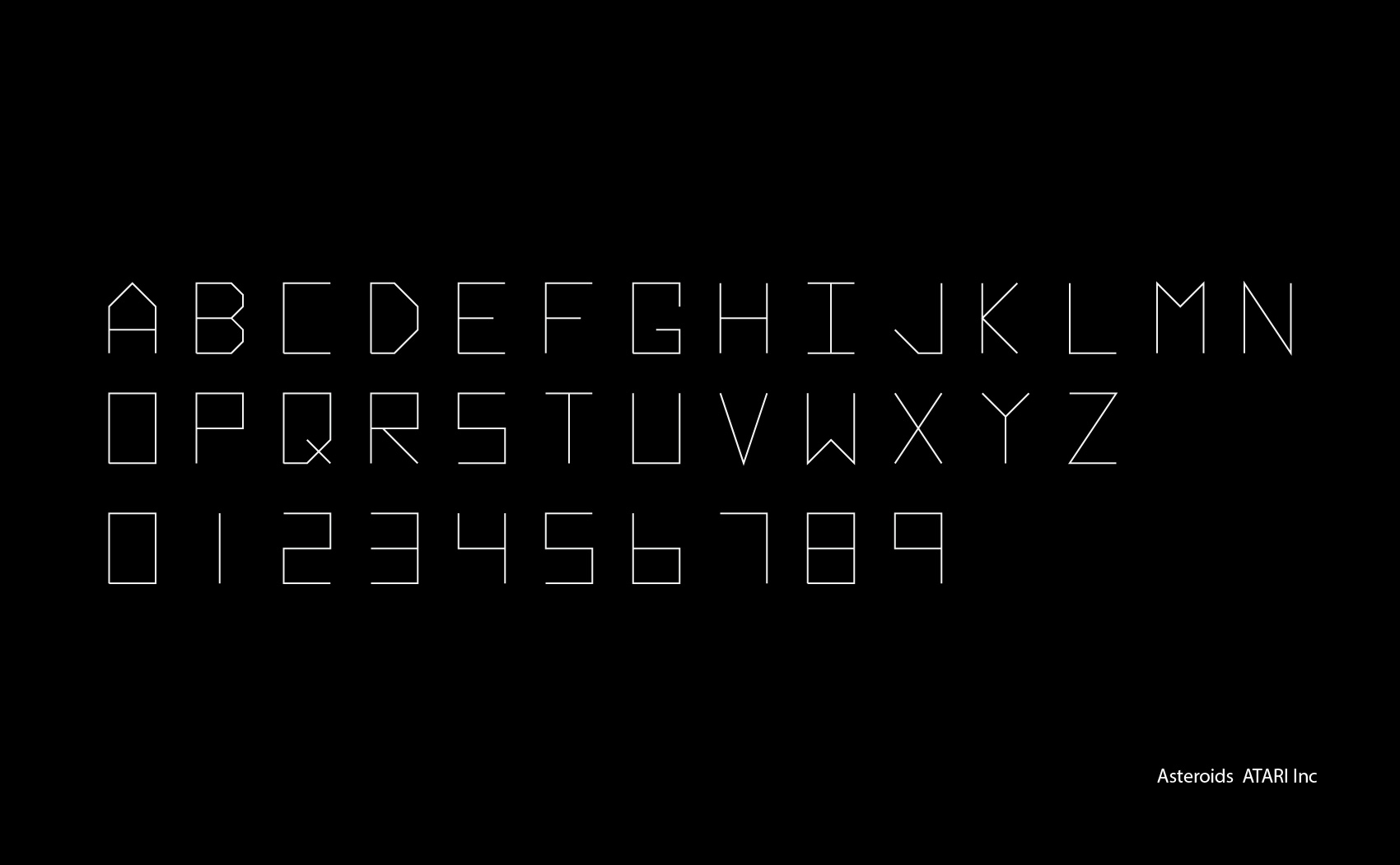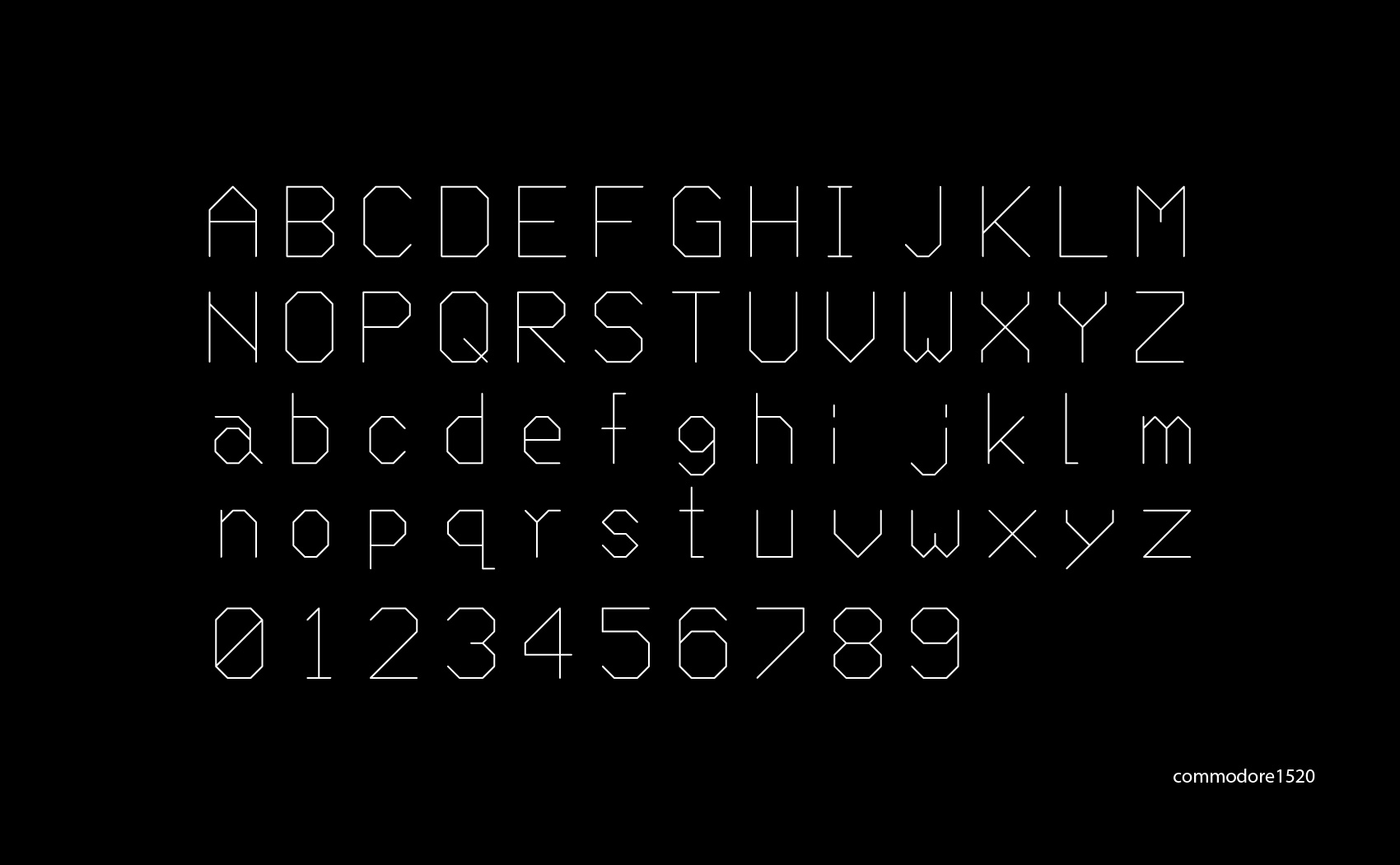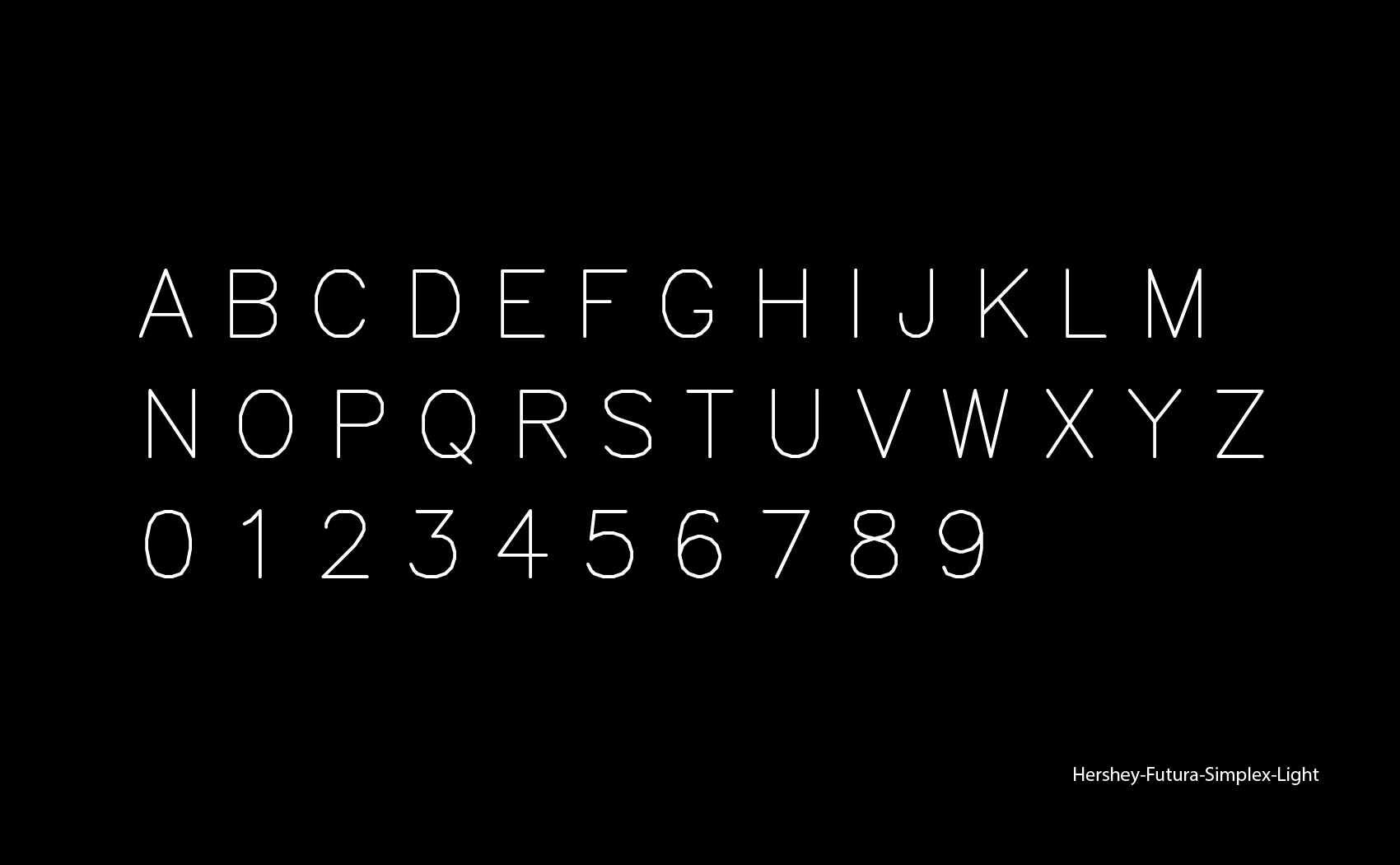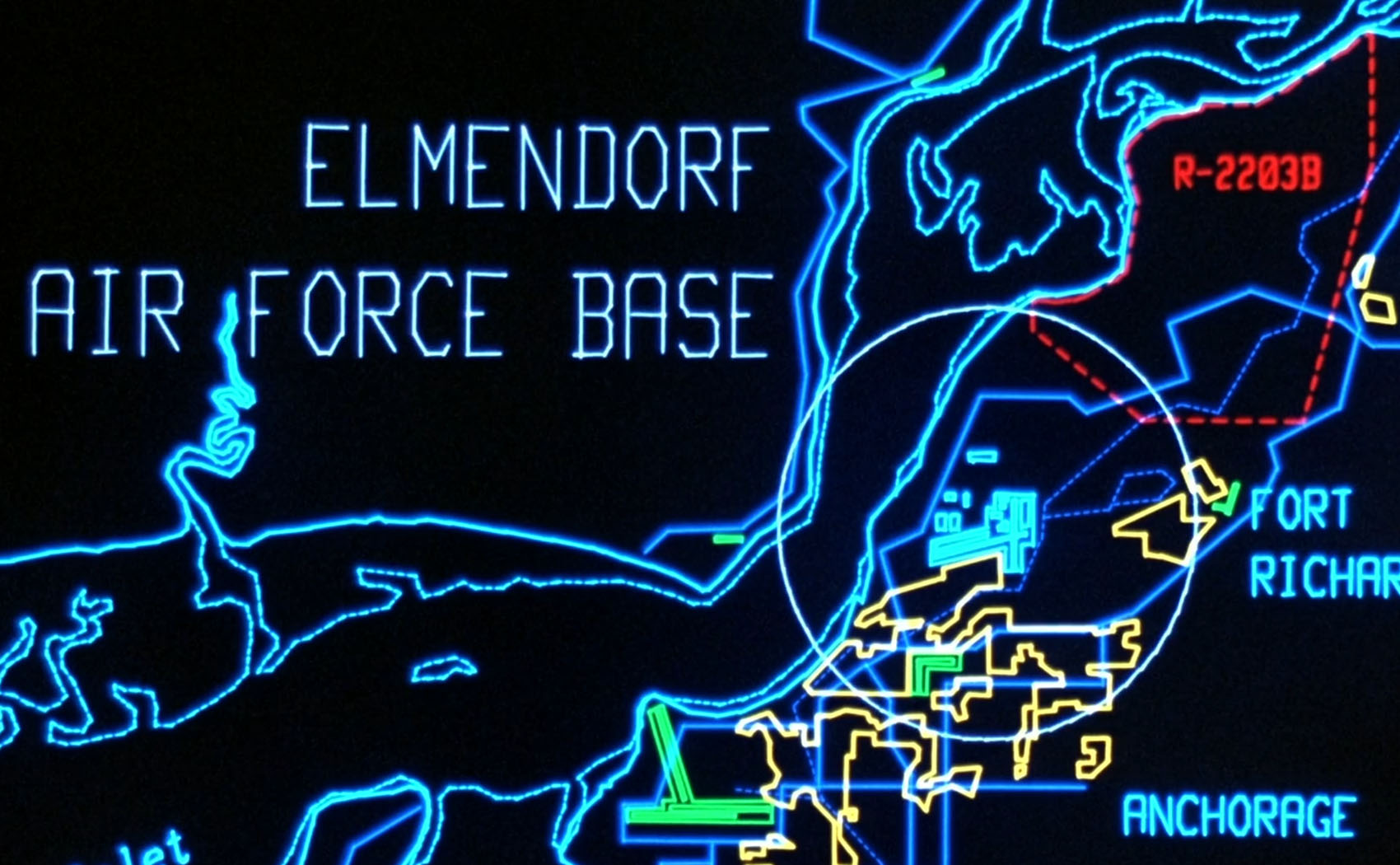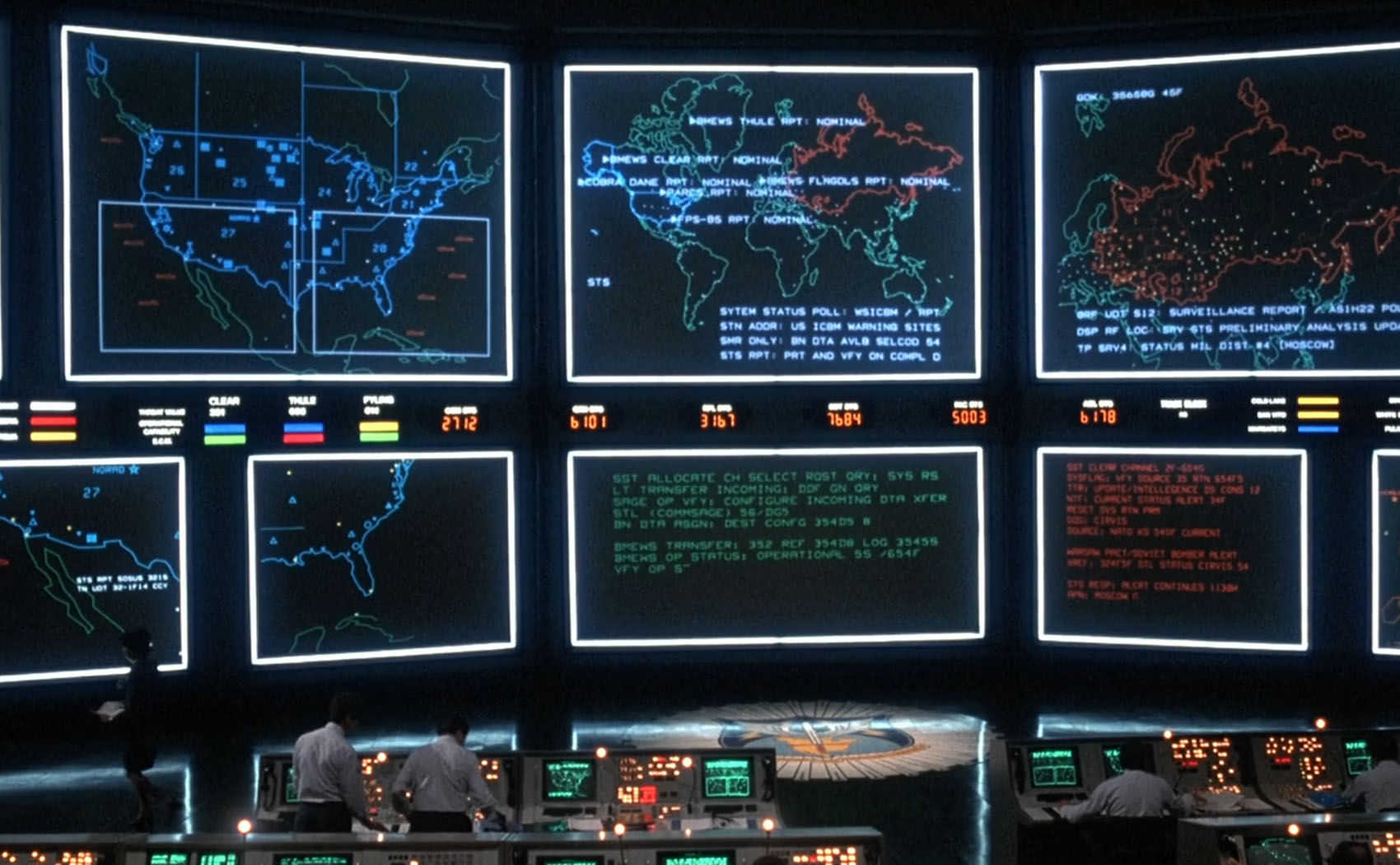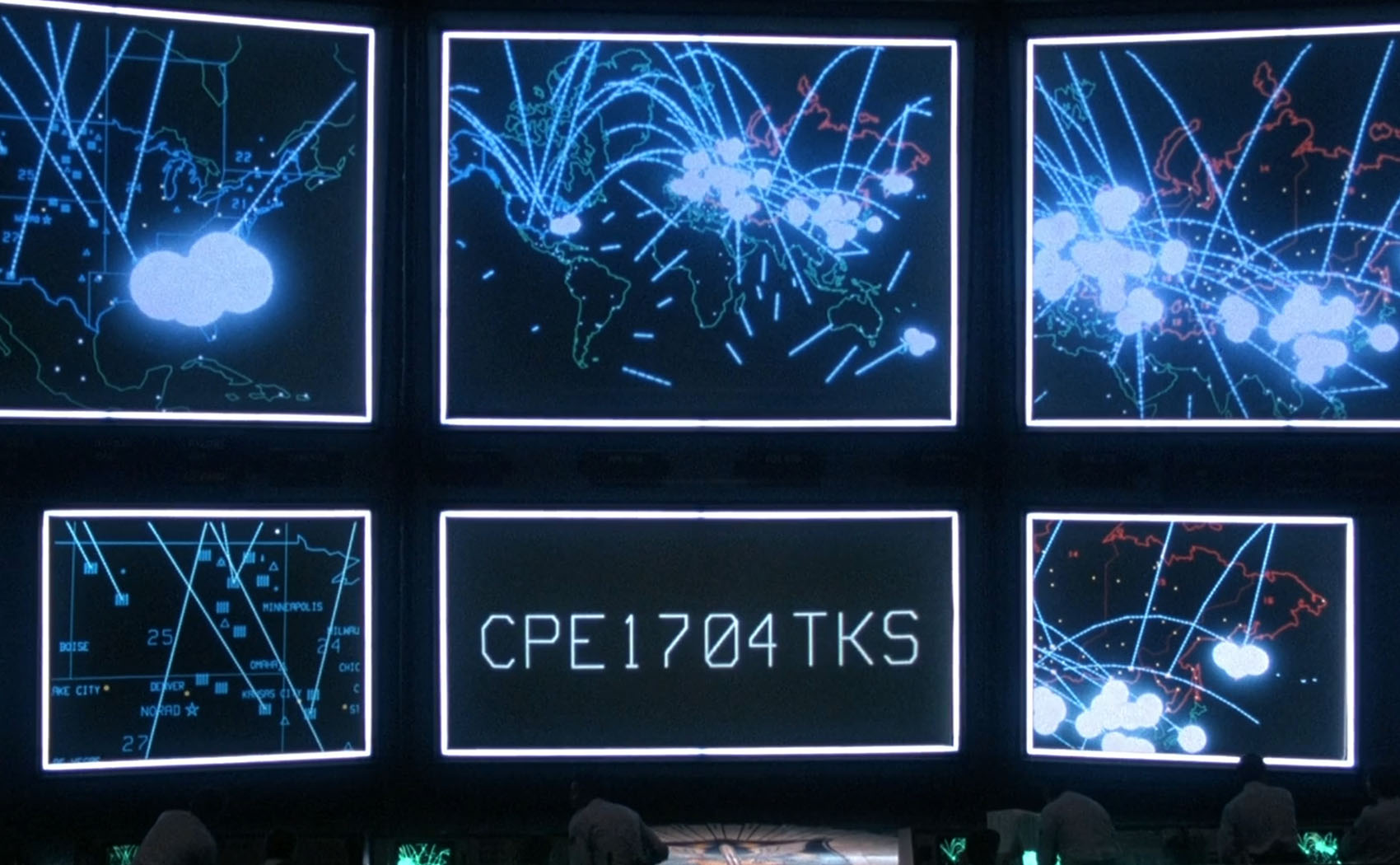
The Future Lost in Type
Vol.02 VECTOR
文字の中に消えた未来 —Vol.02 ベクタータイプ—
モノストロークな未来の香り
『WARGAMES』のメイン舞台はNORAD(北アメリカ航空宇宙防衛司令部) です。そこに設置された戦争シュミレーション用のコンピューター『WOPR』で動くAI「ジョシュア」が暴走して核戦争を起こしかけることを阻止するというのが物語のプロットです。
その舞台となるNORADはメインフレームコンピューターが設置され、複数の超大型の画面と数多くのターミナルの前で忙しく人々が動き回るまさに理想的な最新鋭の軍施設として描かれています。その画面に映し出されているモノストロークで描かれた世界地図、そしてそこにおなじくモノストロークで描かれている文字。今見てもSF的なテクノロジーの気配を感じさせます。
SF映画では宇宙船のコクピットやHUD、戦闘前の作戦会議などの場面で、ワイヤーフレームの3Dや地図などの線画のイラストレーションがよく登場します。『2001年宇宙の旅』や『Star Wars』といった名作が、そういった表現を決定づけ、モニターに映し出されるラインアートは現代ではお約束となって定着している表現です。
現実世界では高解像度のフルカラーのUIが一般的な今日においても、モノストロークで描かれたUIやイラストレーションからはなぜか未来の香りが漂ってきます。そして、「WARGAMES」はさらにモノストロークの文字が加わります。ベクタータイプと呼ばれる曲線を使わず全て直線で結んだこの特徴のあるスタイルは、SFのモノストローク文化とベクター技術が密接に関係しているのです。
ベクターとラスター
1970年代から80年代まで、コンピューターの内容をブラウン管(CRT)で画面表示する方法は大きく分けて2つありました。ラスター方式とベクター方式です。
まずブラウン管は、画面奥の電子銃から電子ビームを発射し、画面内側に塗られた蛍光体に当てて発光させることで映像を表示する仕組みです。2つの違いは、電子ビームの制御方法の違いで、ラスター方式は画面を左上から右下へ向かって高速で走査して、常に面を塗りつぶすように画面を表示します。一方ベクター方式は、必要な線だけをなぞって描く方法です。
半導体メモリの性能が低い時代には、座標のみの情報で済むベクターディスプレイが重宝され、座標間をつなぐ線画の可能性が発展してゆきました。1970年代に入ると安価なメモリのシステムでも複雑な設計図を表示できるようになり実際の建築や航空宇宙設計のCADを用いる現場に革命をもたらしました。それが先端テクノロジーを映し出すイメージとなり、画面に高輝度で描かれるワイヤーフレームはあらゆるSF映画に取り入れられ、70、80年代の近未来のコンピューター画面表現へとつながります。
ベクタータイプフェイス
ラスター方式ではビットマップが文字を表示する最適な方法として定着しましたが、特性の違うベクター方式のディスプレイでも文字を表示する必要性があり文字を作る可能性が探られてゆきます。
ベクター方式は、コンピューターが座標点を指定してディスプレイが電子ビームで線を引くいてゆくためXYの座標点の情報を順番にあたえ、星座のようにして直線で繋ぎ文字を作り上げてゆきます。そして、特性上面を塗ることができないため、技術的な制約が形を作り上げ、この骨格のみのモノストロークのタイプフェイスが生まれました。
CADや製図用のプロッター、アーケードゲームなどの分野で利用されましたが、1980年代の半ばから半導体メモリの性能と価格が劇的に改善し、解像度やカラーの性能の発展性のあるラスター方式が主流となりベクター方式のディスプレイは市場から消えてゆきます。しかし、基本的なアイデアである座標点を数理的に線を結ぶグラフィックの方法は現在のデジタルフォントの中核にしっかりと受け継がれています。
Hershey Fonts
最初期のベクタータイプは 「Hershey Fonts(ハーシー・フォント)」です。アレン・V・ハーシー博士 が 海軍兵器研究所で開発し、1967年に出版された『Calligraphy for Computers(コンピュータのためのカリグラフィー)』で発表したベクターフォントのコレクションです。軍の事務の効率化のため、「CRTプリンタ」というブラウン管と写真を組合わせた技術での組版の研究のなかでベクター方式の文字を研究したそうです。科学者なのですが文字開発に行き着いてしまった、最初期のデジタルフォントのタイプデザイン行った人物です。しかし、侮れないのがその内容で、サンセリフのみならず、ブラックレターやスクリプト体、はては日本語に至るまで研究者のこだわりを感じます。1976年にフォントデータがNIST(アメリカ国立標準技術研究所) によって公開されています。
CAD / プロッター
ベクタータイプが実務で使われたのは1970年代以降のコンピュータ製図のCAD(Computer-Aided Design)の分野です。1970年代に入ると設計業務のコンピュータ化が進み、ベクターCRTとペンプロッターは工業設計の標準出力装置になります。ペンプロッターはCRTのベクター方式と同様でコンピューターの制御で紙に線を引くことができる出力装置で設計や製図などの分野でつかわれています。80年代に入るとPCの一般化に伴って小型のプロッターなどがパソコン周辺機器として登場します。
アーケードゲーム
そして一般的に広まったは70年代後半から80年代のアーケードゲームの時代です。ベクターディスプレイが最も一般の人々を魅了し、クリエイティブに昇華されたのがこの時代です。Atari社やCinematronics社がこの技術をビデオゲームに導入しました。おそらく未来的なイメージの源泉はこの宇宙ものゲーム文化と関係がありそうです。もっとも有名なのが『Asteroids』(1979年 / アタリ) 岩石を破壊していく大ヒットゲームです。文字はゲーム開発の技術者であり、ビットマップと同様に文字の座標情報をいれたデータが表示機材のROMとして備え付けられて使われていました。
演技としてのタイプフェイス
映画『WARGAMES』のNORDのセットの大画面にうつる映像は『HP9845C』という当時最新のグラフィック性能をもつデスクトップコンピュータで制作されたそうです。大画面プロジェクターへは同じくヒューレットパッカード社の「HP 1345A」という超高解像度のベクター表示用モニターをつかってフィルムに撮影したものをプロジェクションしています。ベクターの文字はおそらく映画のためにオリジナルで作られたものでROM由来のものではないようです。さらに、主人公のパソコンの画面がモノクロのビットマップでASCIIアートのようにゲームを表示していたのとの対象的に、カラフルなグラフィックと毛色の違うベクタータイプを大写しで最後に持ってきたことは、とても文字を重視した演出のように感じます。
そして、『WARGAMES』のラストシーンは、核ミサイルの発射コードを解こうとAIが総当たりで必死に解析している表現として、10桁の文字と数字をランダムに表示する緊迫のシーンがあります。人間の演技ではなく冷徹なコンピューターの演技としてこのベクタータイプフェイスが人々の目を惹きつけます。角ばった字形とランダムに変化するモーショングラフィックスは、40年の時を超えてもなおコンピューターをコンピューターたらしめるカタチをしているように思えてくるから不思議です。過去の人々が夢見た未来に到達した今でも、タイプフェイスが同じイメージを運んでくるこの「未来の香り」の謎はコンピューターという常に塗り替えられる技術の見ることのできない概念にあるのではと考えてしまいます。